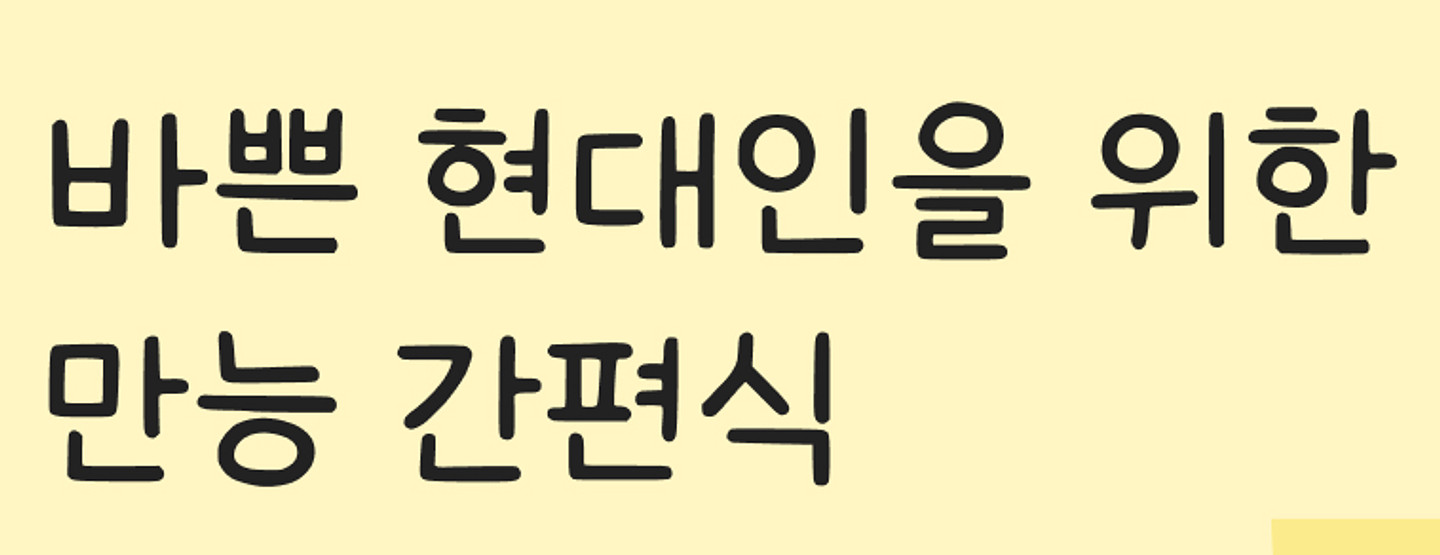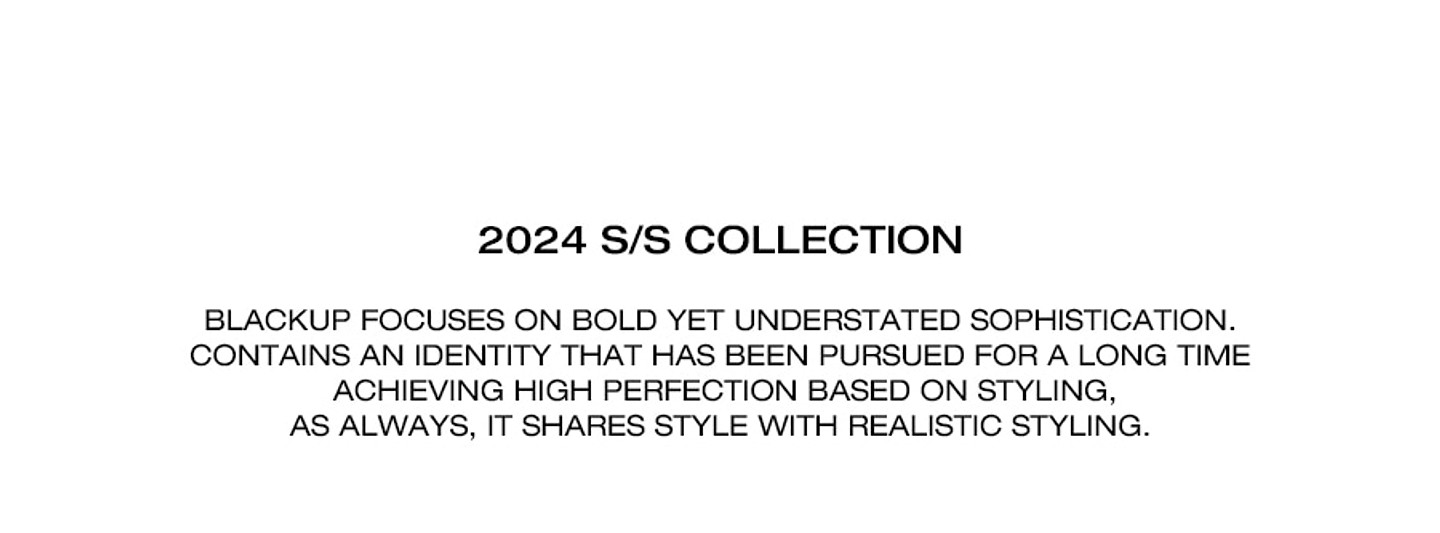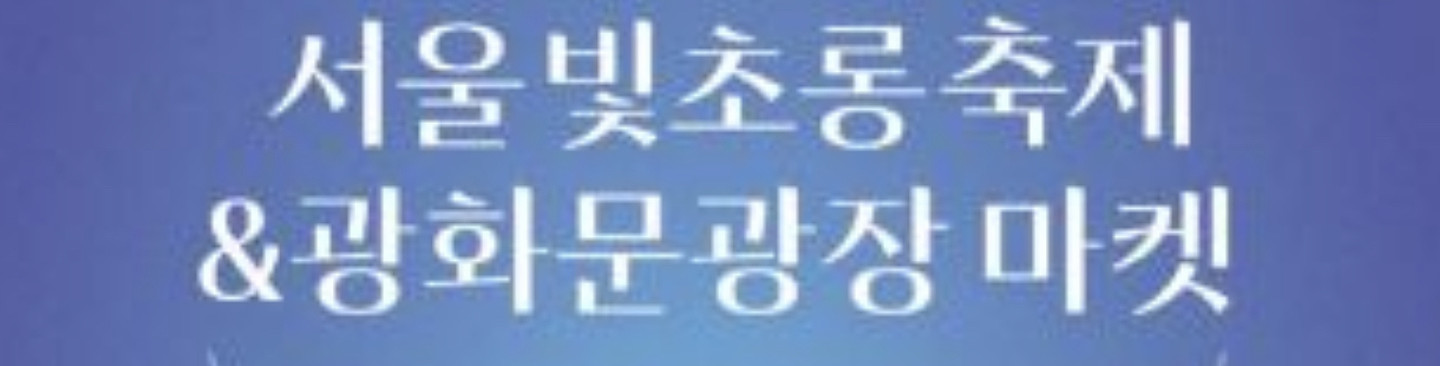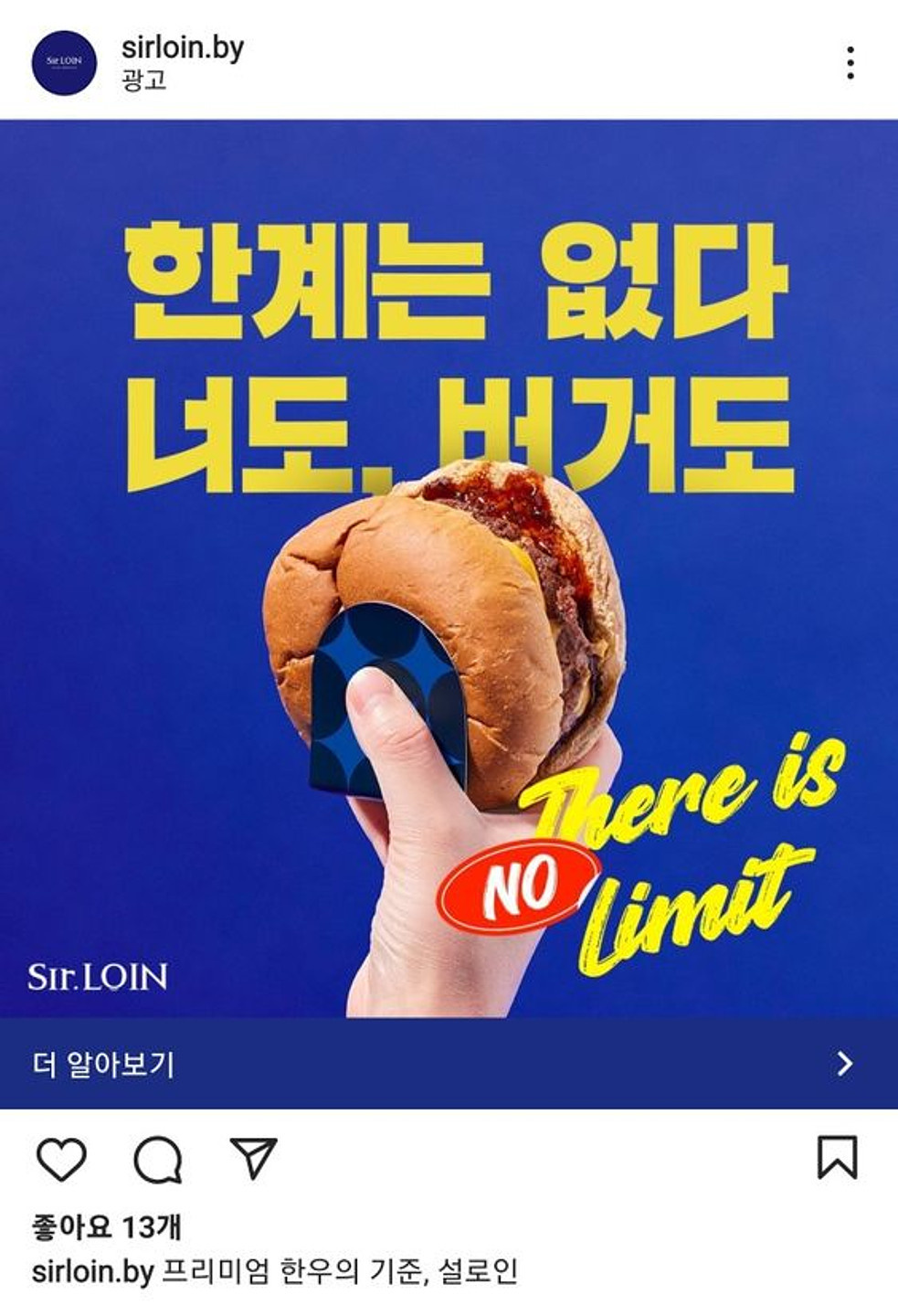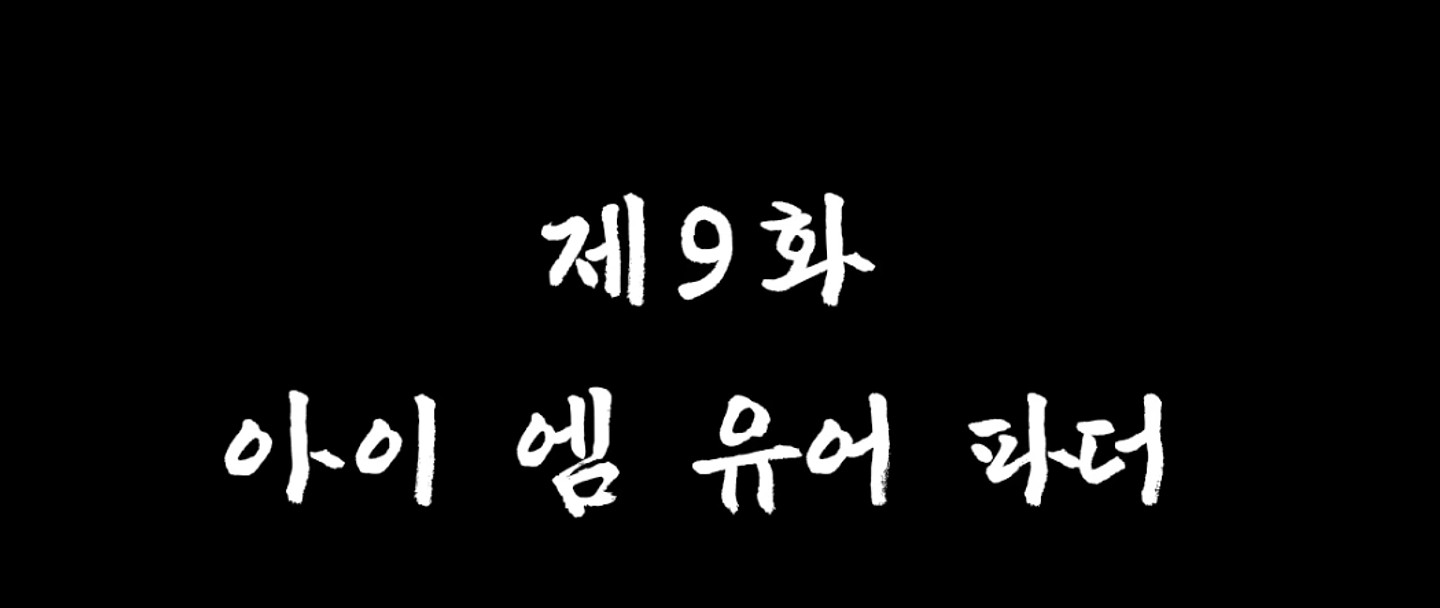
이 폰트 뭘까욤...
폰트 이름이 뭘까용...?
한글폰트 알려주시면 감사하겠습니다!
머드 폰트 알려주세요
폰트 알 수 있을까요?
언젠가 그가 너를 맘 아프게 폰트 뭔가요?
영어 폰트를 찾고 싶어요. 둥근 곡선과 a u g 등 직선이 조화된 폰트가 필요합니다!
'그리스어'인데요, 여기에 사용된 폰트가 궁금합니다. 아무리 찾아도 나오지 않네요.
이거 폰트 아시는 고수분 계신가요 ㅜㅜ 젭알 도와주세욤..
배경 폰트랑 영어로 작성된 런투패밀리 폰트, 하단에 '런투패밀리' 총 3개의 폰트 정보가 궁금해요
이 폰트 먼가요ㅠㅠㅠㅠ?????
이 폰트가 너무 궁금해요 ~~~!!
이 폰트 뭔지 아시는분 !
유튜버 히카님 폰트입니다 이거 무슨 폰트인지 아시는분
이 폰트 너무 이쁜데 혹시 무슨 폰튼지 아시는분있으면 알려주세요ㅜㅜ
https://www.youtube.com/watch?v=BaGIFOmDlTk&list=WL&index=22&t=64s 이청아 유투브에 나온 폰트인데 어떤 폰트일까요? 지마켓산스보다는 정갈한 느낌인데....
이런 폰트 찾고 있습니다
엔믹스 별별별 폰트 뭔지 알 수 있을까요? 비슷한 폰트라도요 !!
무슨 폰트 일까요..?
안녕하세요 이 폰트 정보를 알수있을까요??
이 폰트 혹시 무엇인지 알 수 있을까요?
온글잎 같은데 뭘까요..? 100페이지까지 뒤져봣는데 못찾았어요..
이거 폰트 뭐에요~?ㅠㅠㅠ
이비온님 영상입니다 혹시 이폰트가뭐에요?? ㅜㅜㅜㅜ
대화창에 있는 폰트 무슨 폰트일까요?
한글 무슨 글꼴인지 알려주세요~
폰트 찾아요
이 폰트가 뭔지 모르겠습니다!
여기 '여기어떄 연말결산' 폰트가 뭘까요??
KoreanYASSR Regular 라는 폰트인거같은데 한글로 무슨체인지 알수있을까요????
책은 아라의 소설입니다. 책 본문 무슨 폰트인지 알려주세요ㅠ
GURO 저 폰트 어떤 폰트 인가요? 한글로 썼을때 저렇게 비슷하게 나오는 폰트 있을까요?
여기 '더블유데이' 폰트가 뭘까요...?
폰트 정체 알고싶습니다!!!!
무슨 폰트인가용?
이 폰트 뭘까요..?
영문폰트 궁금해요!ㅠ
이것은 무슨 폰트 입니까?
이 폰트 어떤건지 아시는 분 있으실까요?
이 폰트 아시는 분 있나요ㅠㅠ -출처 : 인스타 글
Elefhant 폰트 정말정말 궁금해...ㅜ
웹툰에서 자주 보이는 글꼴인데 이 글꼴이름이 뭔가요?
이거 무슨 폰트인가요?!
무슨폰트인가요???
뭘까용...ㅠ 부탁드립니다
Beauty,907 이거 폰트좀 찾아주세요
이 폰트 뭘까요??
핀터레스트에서 찾은 디자인인데 저희 디자인에 이 폰트를 도입해보고 싶어서 질문 드립니다
오래전에 사용했던거라서 기억이 안나요
이거 무슨 폰트죠..?
폰트명이 뭘까요? 상업적으로 사용이 가능한지 해서요-!
이거 분명 무료 폰트인데 뭔지 아시는 분
금괴가 없잖아? << 이 부분의 폰트가 궁금합니다 예전에 한번 다운 받은 적이 있었던 것 같은데. 이름이 생각이 안나요ㅠ 꽃으로 시작하는 이름의 폰트였는데 눈누에서 못 찾아서 질문 올려요ㅠㅠ